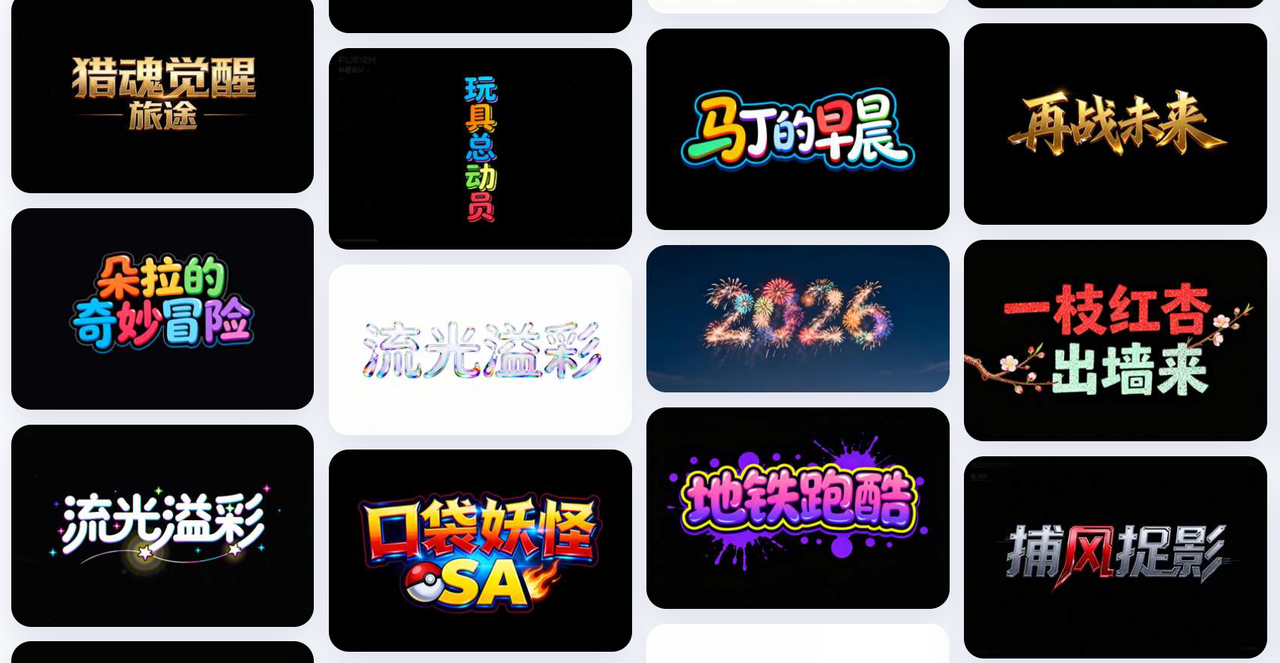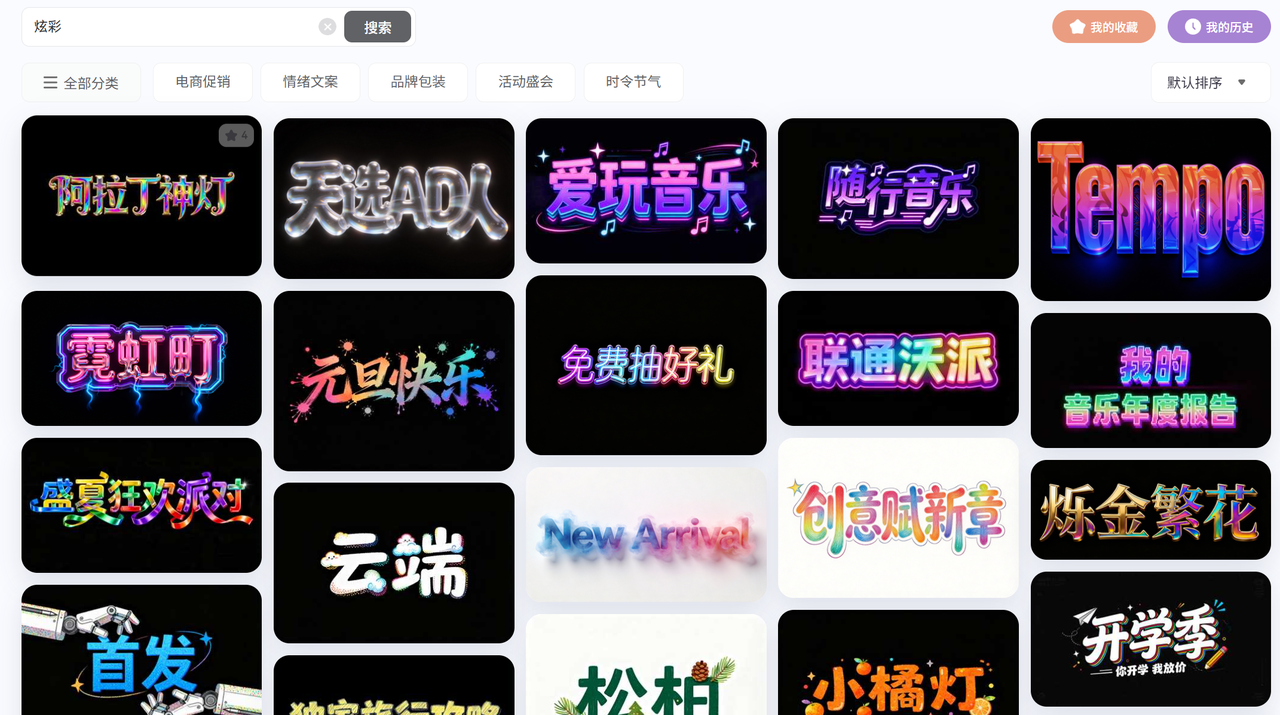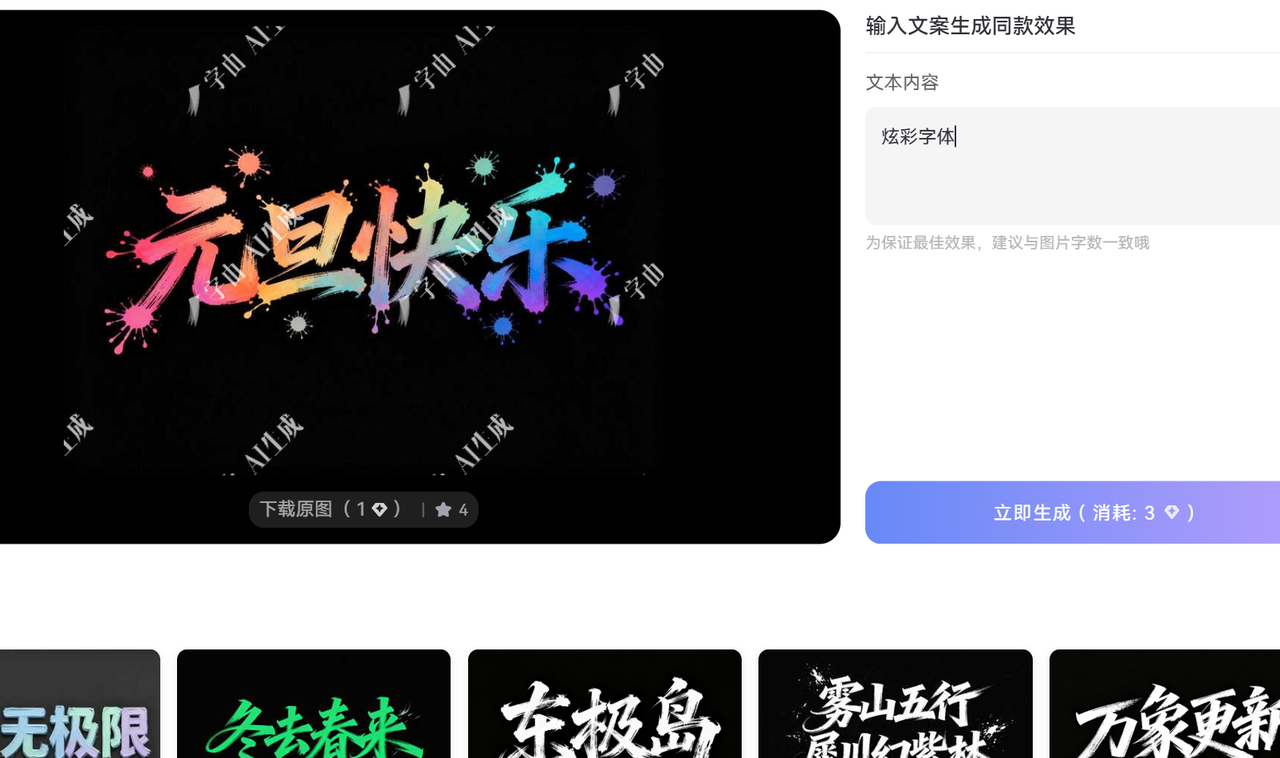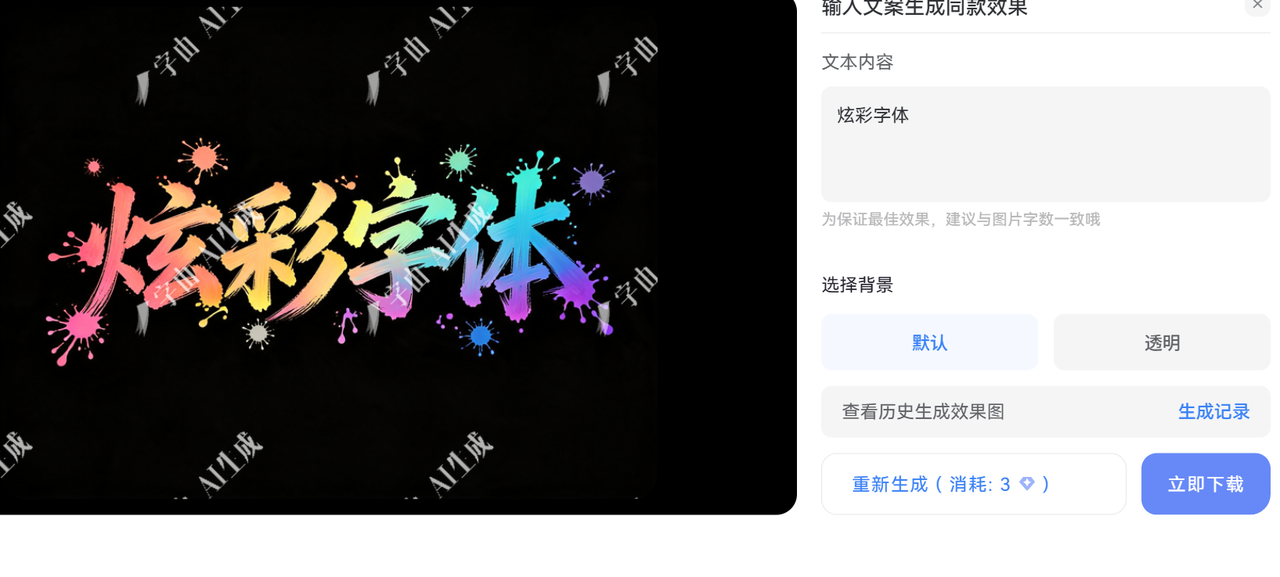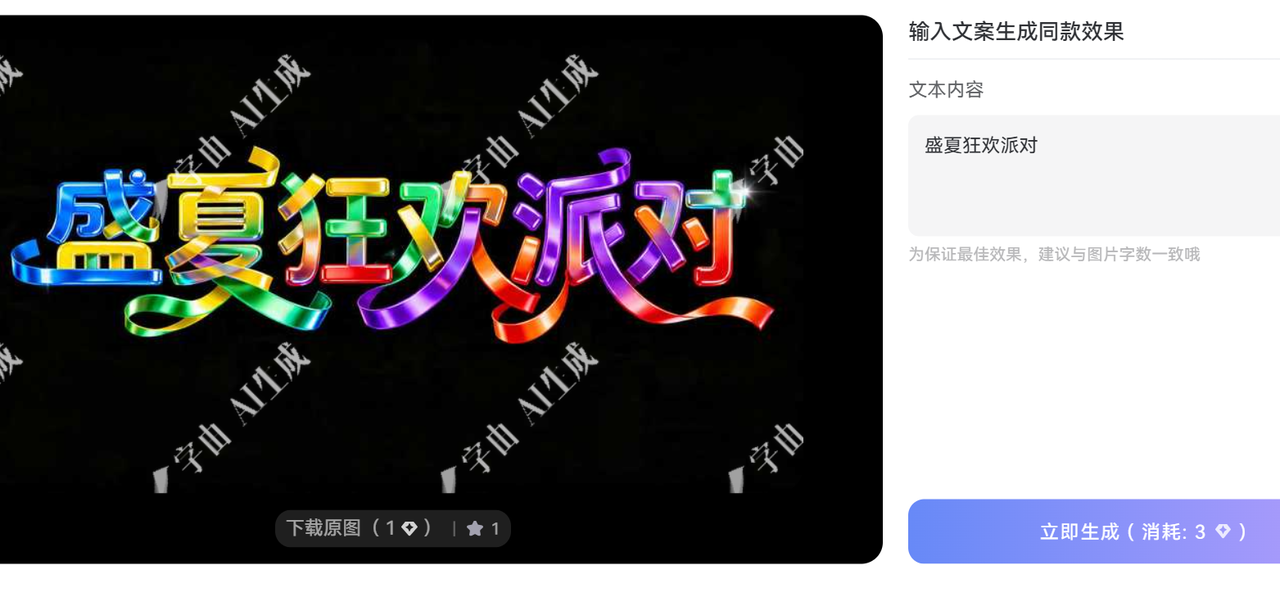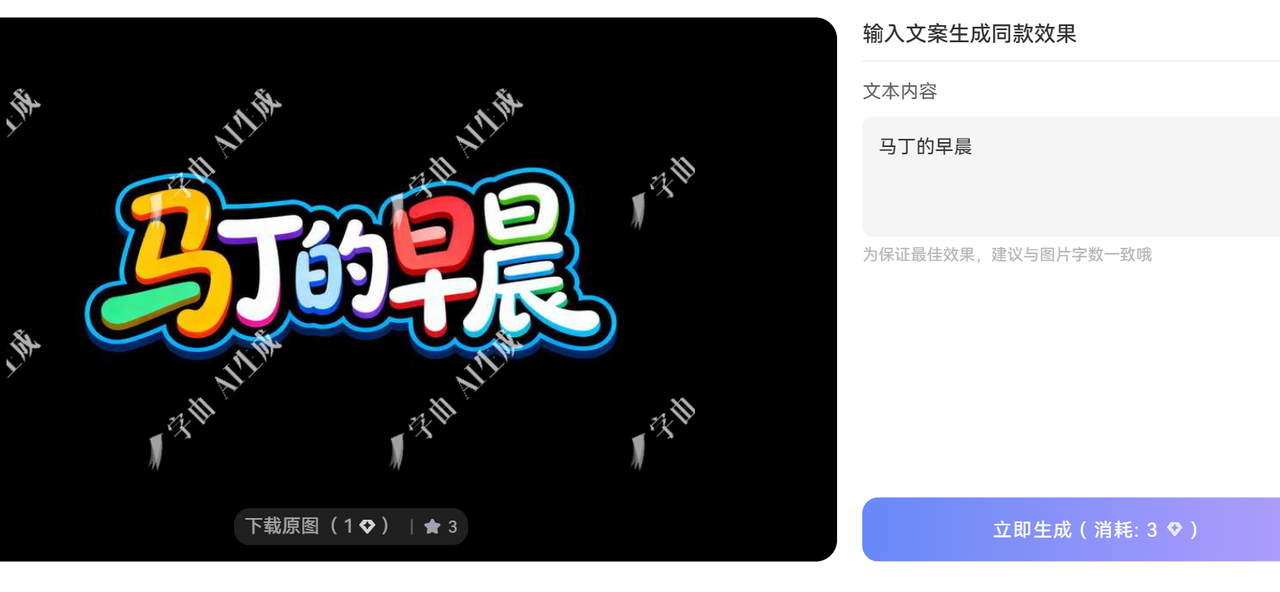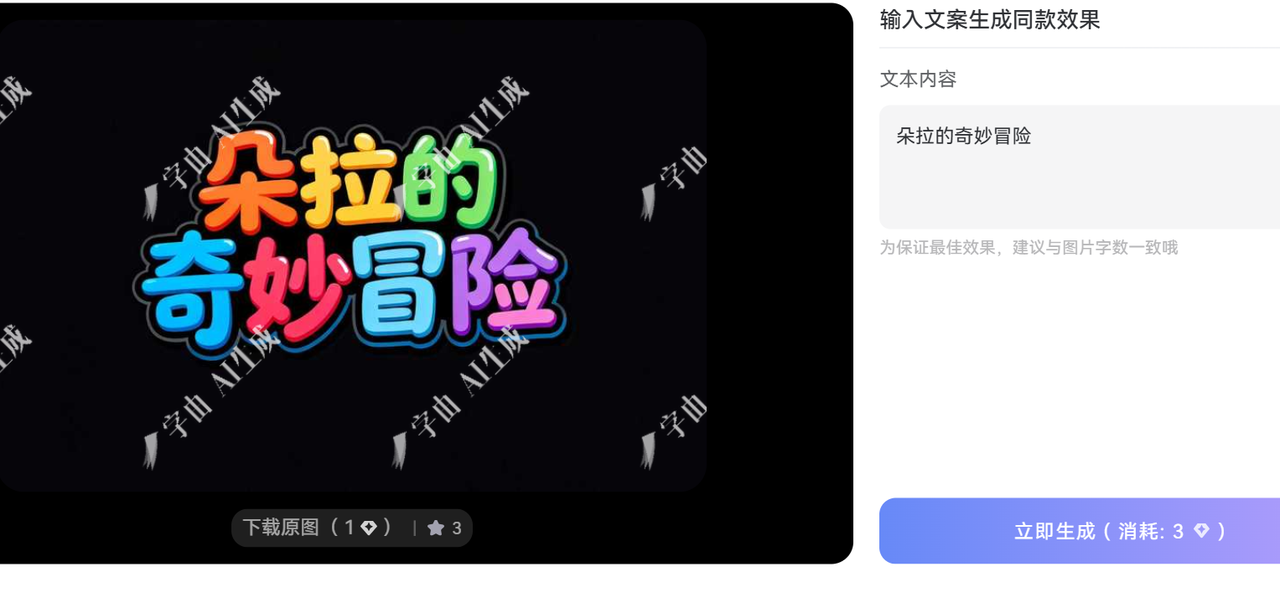
对于设计师或者自媒体博主来说,想要找到那些既好看、有视觉冲击力,又能安全商用的“炫彩字体”,简直像在大海里捞针。市面上好看的炫彩字体大多是国外设计师做的,版权路径复杂;国内的商业字库虽然好,但动辄几百上千一年的授权费,对个人或小工作室来说确实是一笔不小的开支。
如果你也正面对着这些困扰:
1. 想要炫酷的标题,但自己用PS慢慢磨渐变效果太费时间。
2. 害怕误用侵权字体,每天过得战战兢兢。
3. 审美疲劳,觉得传统的黑体、圆体太单调,抓不住读者的注意力。
那么,我今天分享的这个方法,可能会彻底改变你的工作流。通过字由AI字体,我实现了真正的“炫彩字体自由”。这不仅解决了版权隐患,更让我的出片效率提升了。
在使用字由AI之前,我一直觉得文字设计是一个体力活。我们要先选好基础字体,再叠加图层样式,调渐变、加高光、做投影。如果文字内容改了,所有的效果还得重来一遍。
免费商用的炫彩字体下载教程
1. 进入AI创作大门
2. 在搜索框搜索“炫彩”
获得所有炫彩相关字体的模板
比如你想做一个“年中大促”的标题,或者是一个“夏日派对”的封面。建议文字不要太长,4到6个字的效果是最好的,视觉冲击力最强。
3. 挑选你的“炫彩”风格
选择一款你喜欢的字体模板,替换自己的文字,就可以一键生成同款炫彩字体
4. 下载炫彩字体
推荐几款我常用的炫彩字体
盛夏狂欢派对
马丁的早晨
朵拉的奇妙冒险
使用的小心得
在使用字由AI制作炫彩字体时,我也总结了几个能让效果翻倍的小技巧:
• 字数少胜于字数多:炫彩效果本身就很抢眼,如果字数太多,画面会显得乱。
• 背景的反差:如果你的字体是亮色的炫彩,背景尽量选深色或者纯色,这样才能把那种光感衬托出来。